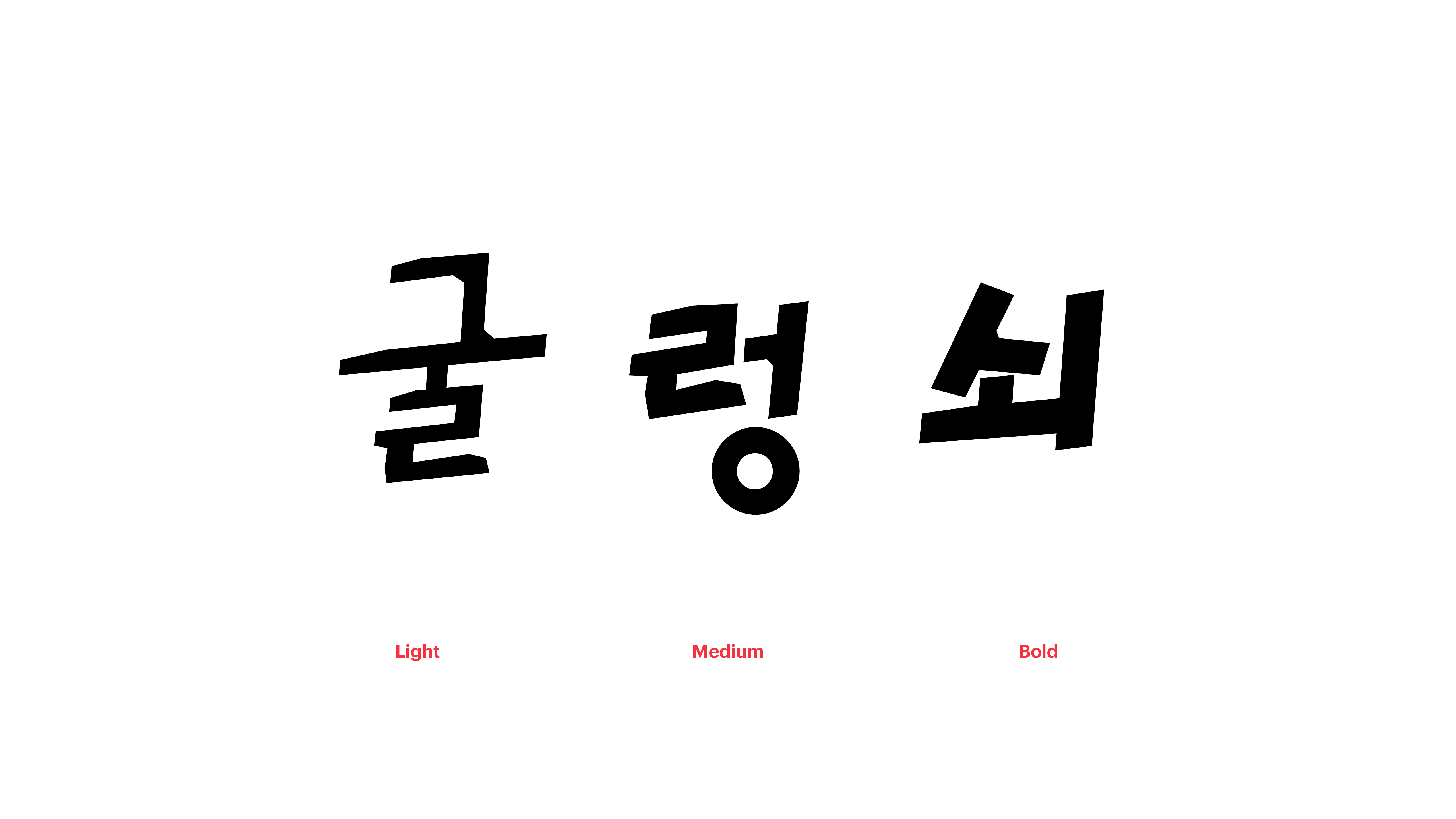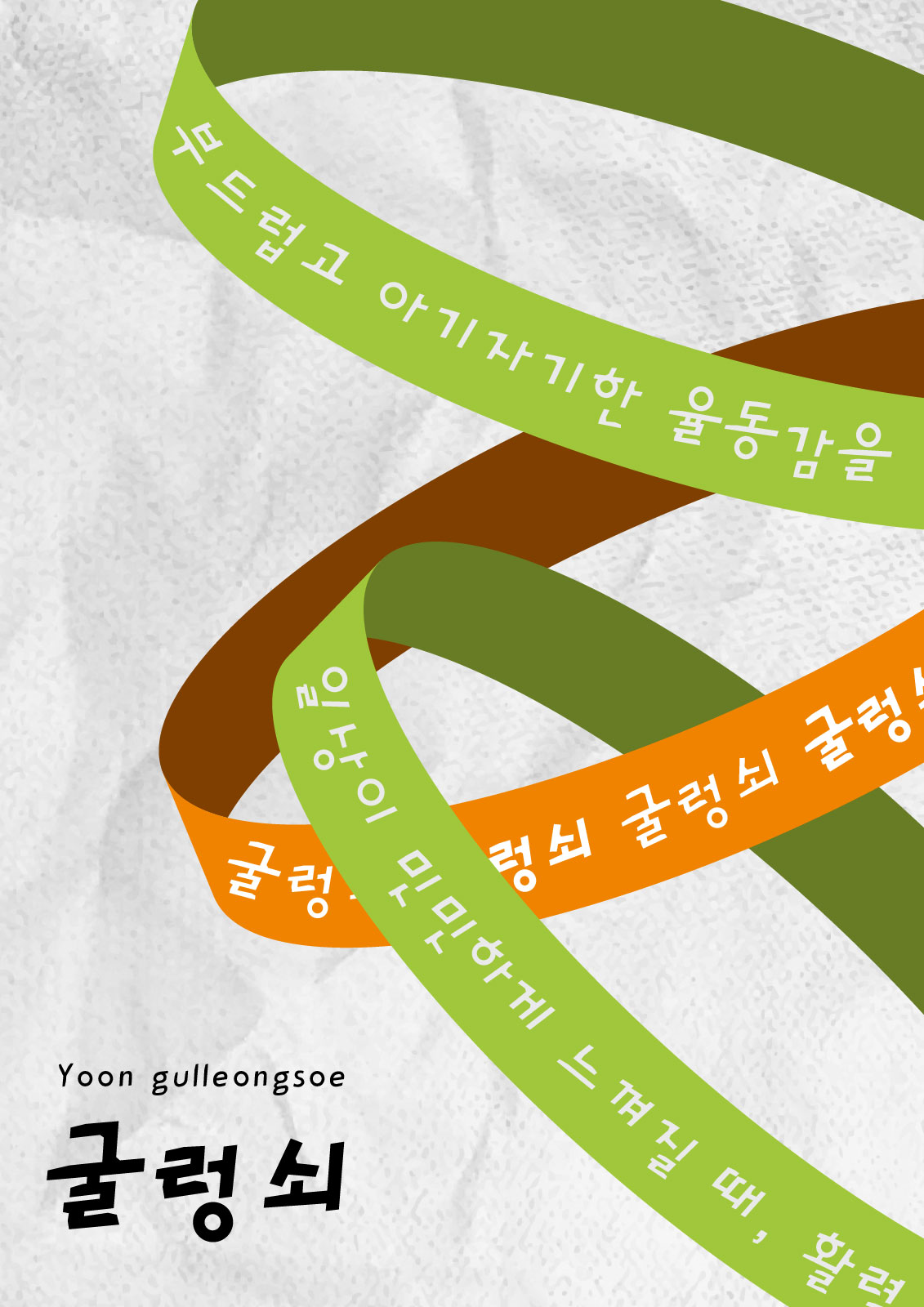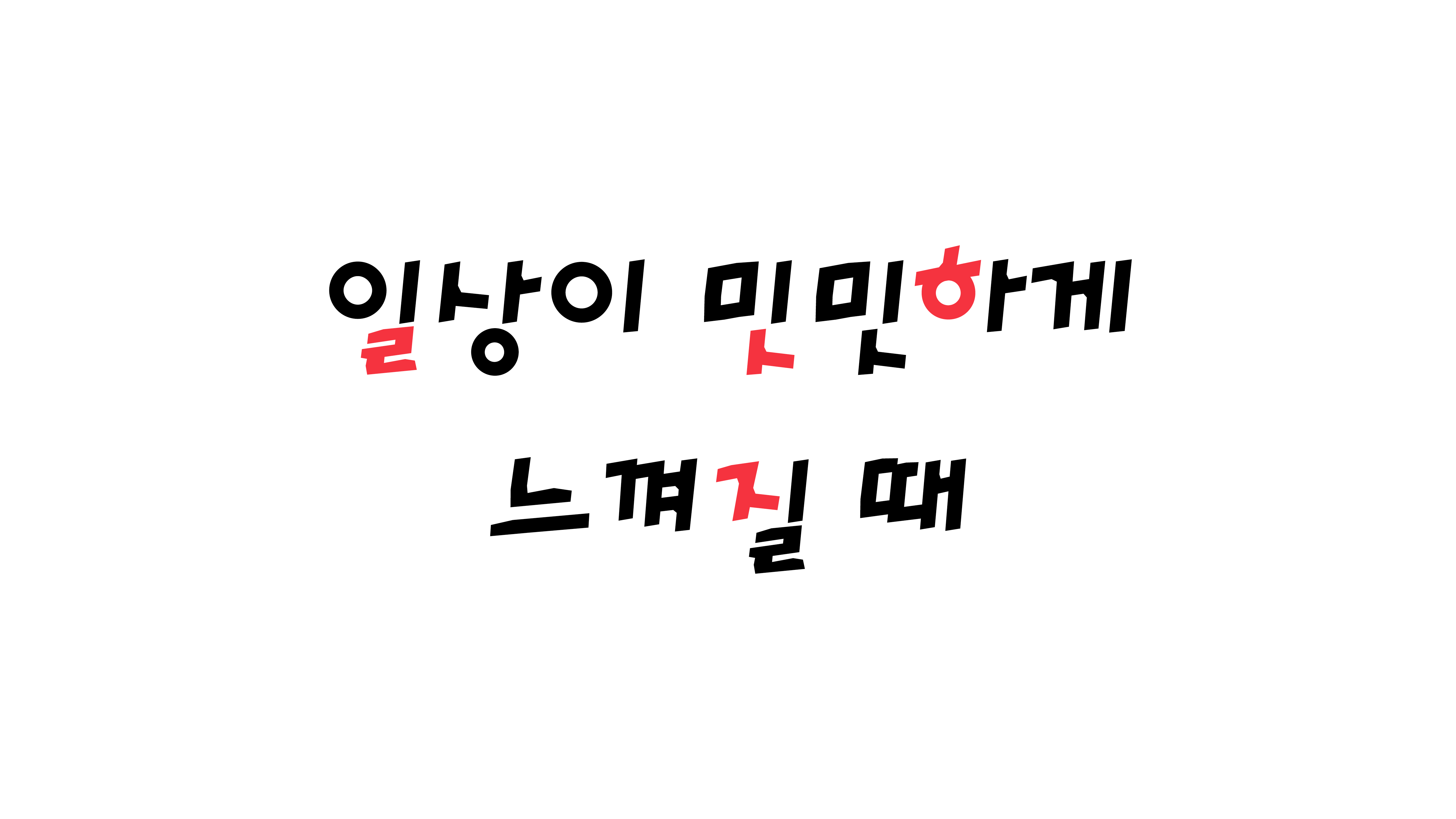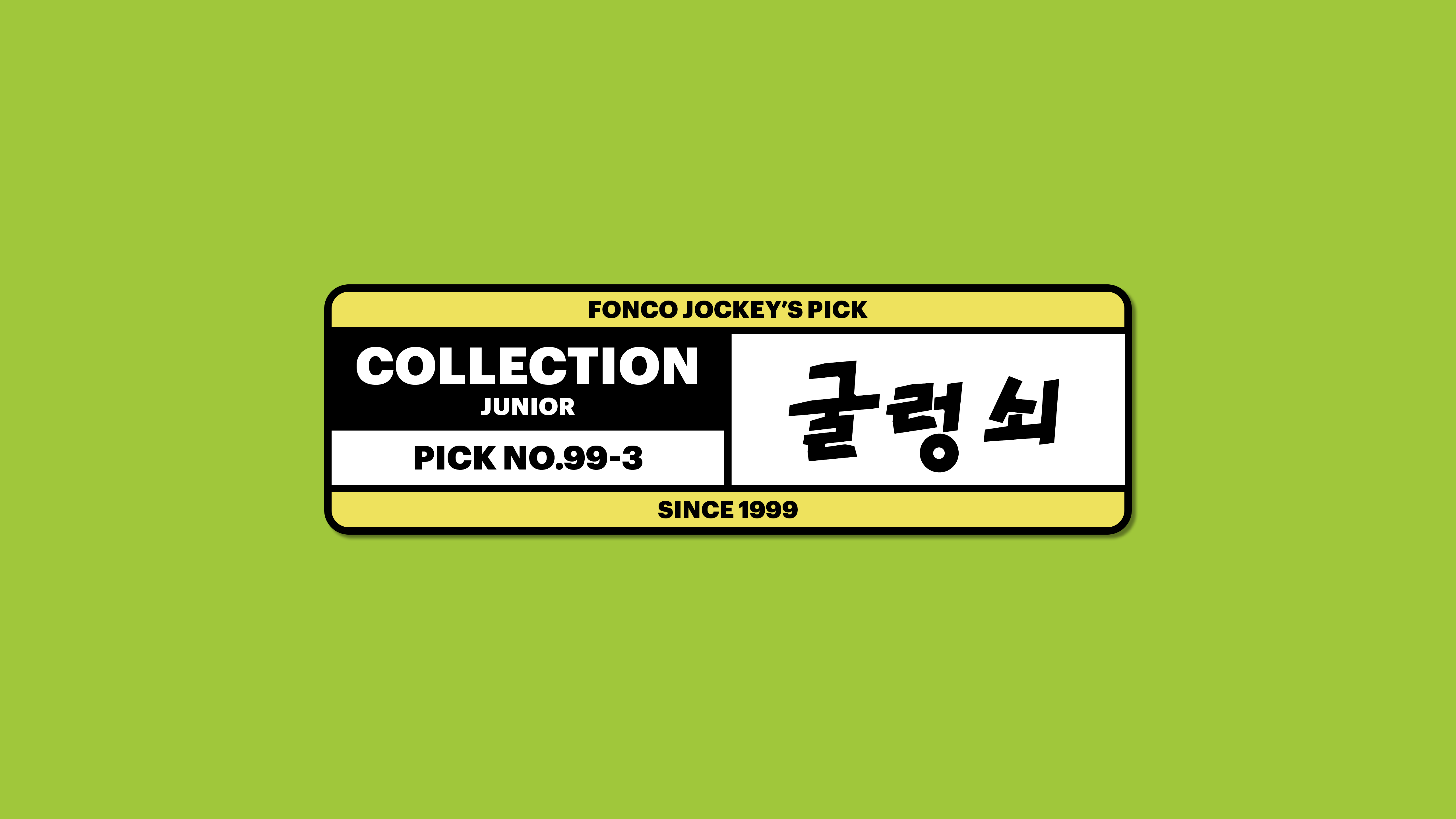
굴렁쇠
Yoon 굴렁쇠
굴렁쇠체는 부드럽고 아기자기한 율동감을 지닌 폰트입니다. 굴렁쇠를 굴리며 지나가는 어린아이를 본 것처럼, 기분 좋은 웃음이 피어나지요. 폰트를 구성하는 개별 요소들에 디테일한 기울기를 부여하여 활기찬 느낌을 한껏 끌어 올렸습니다. 일상이 너무 밋밋하게 느껴질 때, 활력 충전용으로 처방하세요!